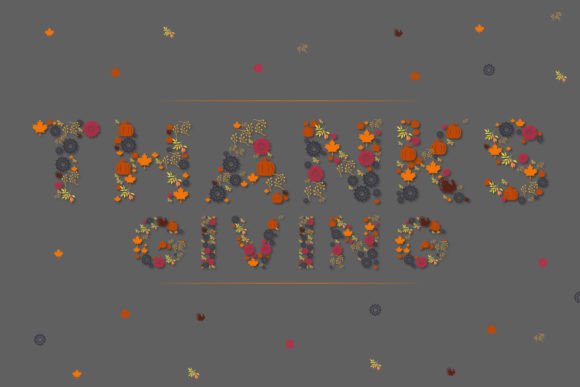
Thanks Giving Vector Font Alphabet
Việc tìm kiếm các thành phần thiết kế phù hợp có thể là một thách thức, nhưng Thanks Giving Vector Font Alphabet cung cấp một bộ sưu tập đặc biệt giúp nâng tầm công việc của bạn ngay lập tức.
Được chế tác với độ chính xác cao, Thanks Giving Vector Font Alphabet cung cấp các vector sạch, kiểu chữ mượt mà và giấy phép thương mại để bạn yên tâm.